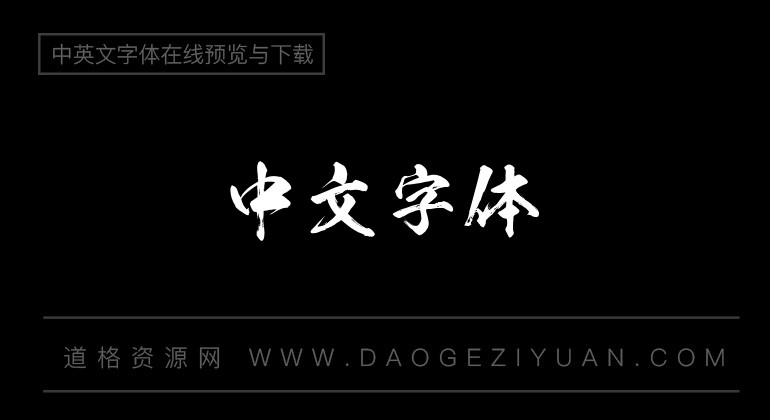
经典毛笔字体
经典毛笔字体是一种传统的中国书法字体,它源于汉字的书写形式,以毛笔写成。它有着浓郁的中国传统文化气息,传承了中国书法的精华。经典毛笔字体有着独特的风格,一般具有横笔画粗、竖笔画细、字迹稳定、笔画清晰、收尾圆润等特点。它的字体比较端庄大方,能够很好的表现出中国文化的韵味。
经典毛笔字体是一款非常不错的手写艺术字体,具有很好的视觉感,适合于文化类的宣传设计、商业类品牌的广告和产品包装设计以及个性化文字排版等较多场景。
经典毛笔字体字符映射图